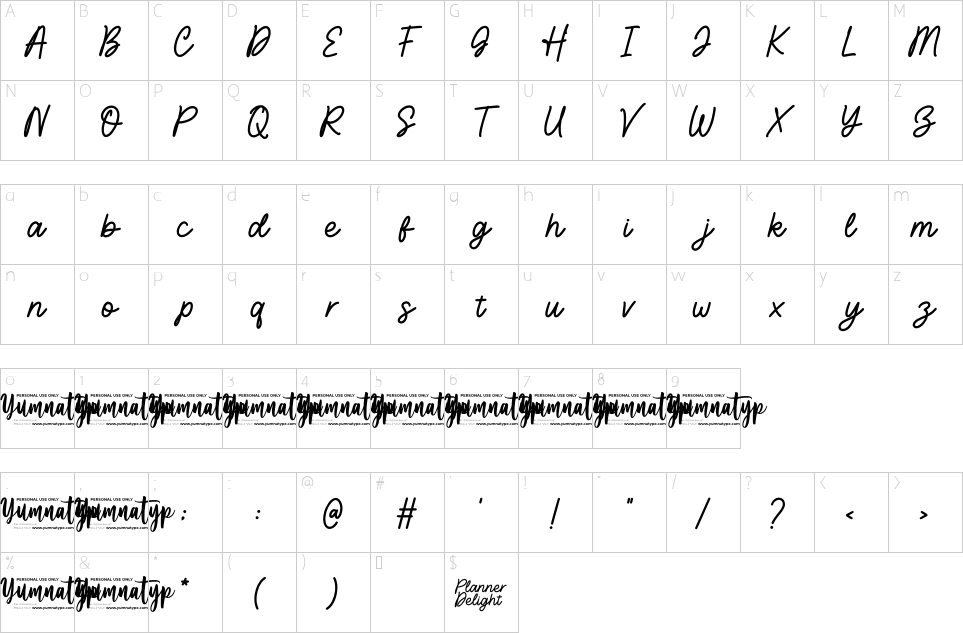
A Planner Delight é uma fonte elegante e acessível, perfeitamente adaptada para uso em projetos gráficos pessoais ou corporativos. Desenvolvida pela Yumna Type, esta fonte livre de registro está disponível tanto para uso em dispositivos Windows quanto Mac. Sua simplicidade e facilidade de uso tornam-a uma ótima escolha para designers que buscam uma fonte moderna e eficiente para seus projetos diários. Com seu design minimalista, Planner Delight adiciona um toque agradável a qualquer projeto, garantindo que sua mensagem seja notada. Se você está procurando por uma fonte de qualidade que não custa nada, a Planner Delight é uma excelente escolha. Com seu design claro e versátil, esta fonte de 1001 Free Fonts certamente merece um lugar na sua coleção.